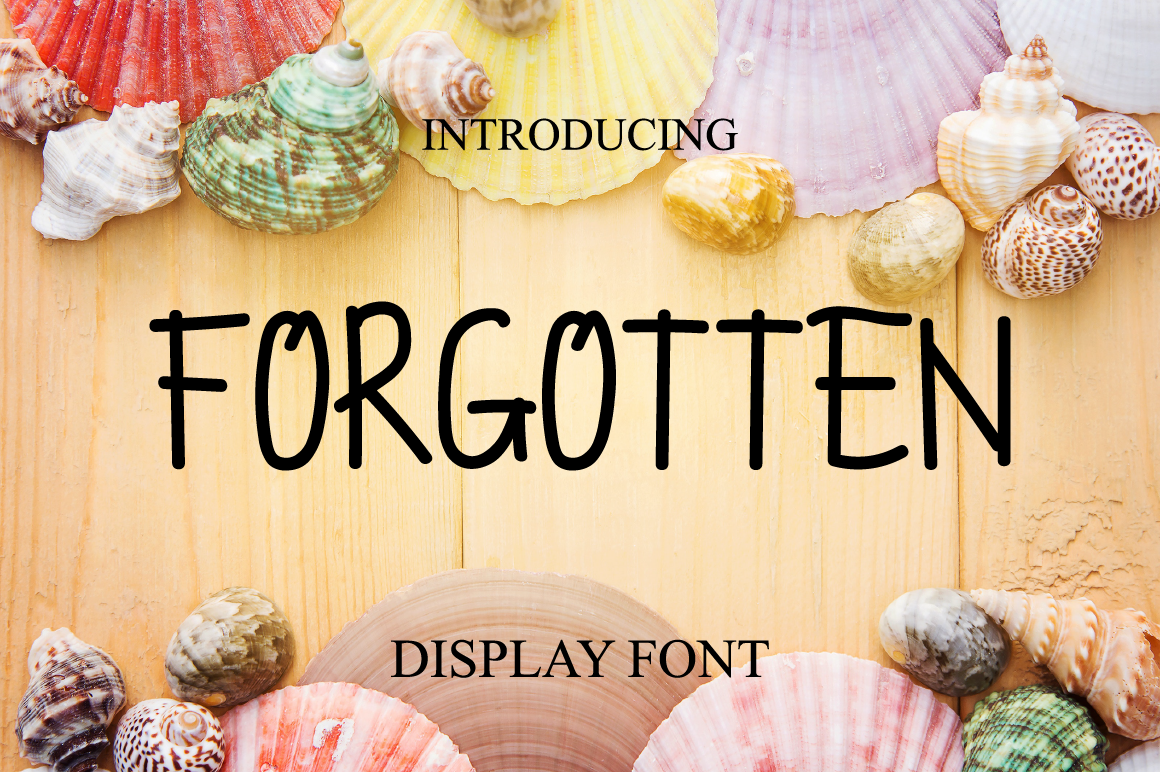
A fonte ‘Forgotten Typeface’ é uma escolha perfeita para quem busca uma mistura harmoniosa entre a elegância dos caracteres digitais e o encanto do estilo livre ou escrita à mão. Desenvolvida pelo designer fanastudio, esta fonte pertence à categoria de fonts manuscrits. Não é apenas um esquema de escrita digital refinado e funcional; é uma paixão em concreto que se materializa nas letras. O design de ‘Forgotten Typeface’ transmite um encanto único, com linhas suaves e traços delicados que remetem à arte da escrita livre. Ela tem um toque natural e autêntico, como se tivessem sido criadas a partir dos dedos de alguém experimentando o processo de escrever em papel, sem pressa nem preocupações estilísticas. Embora seja uma fonte digital, cada caractere parece ser um ato pessoal, contendo nas linhas e nos espaçamentos pequenos detalhes que remetem à forma como os humanos expressam pensamento e emoção por meio do papel. Sua simplicidade não diminui sua riqueza de significado, oferecendo uma linguagem poderosa para o designer que busca um toque único em seus projetos. Essa fonte é especialmente útil para quem deseja dar ao seu design um tom mais pessoal e autêntico, onde as linhas expressam sentimentos e experiências do autor de maneira inconfundível. Se você está buscando uma fonte que seja mais que apenas uma ferramenta de escrita digital, ‘Forgotten Typeface’ é uma escolha sensata para explorar sua versatilidade em diversos ambientes de design.